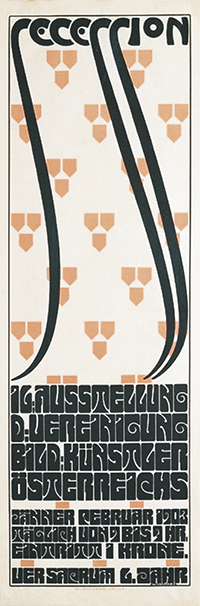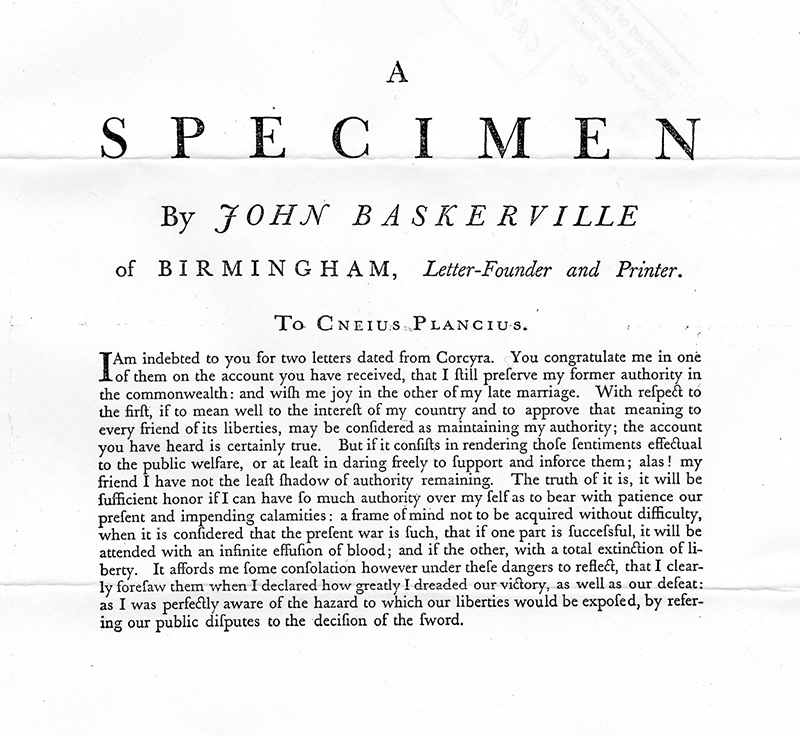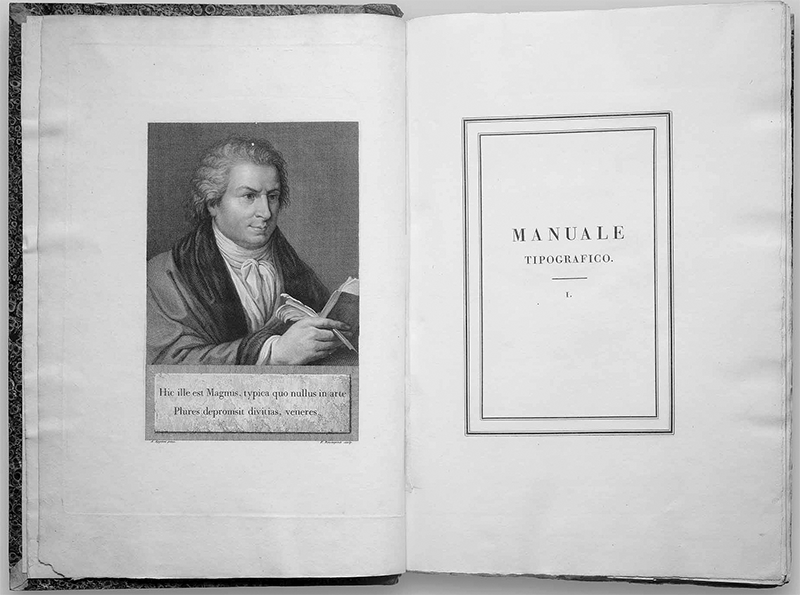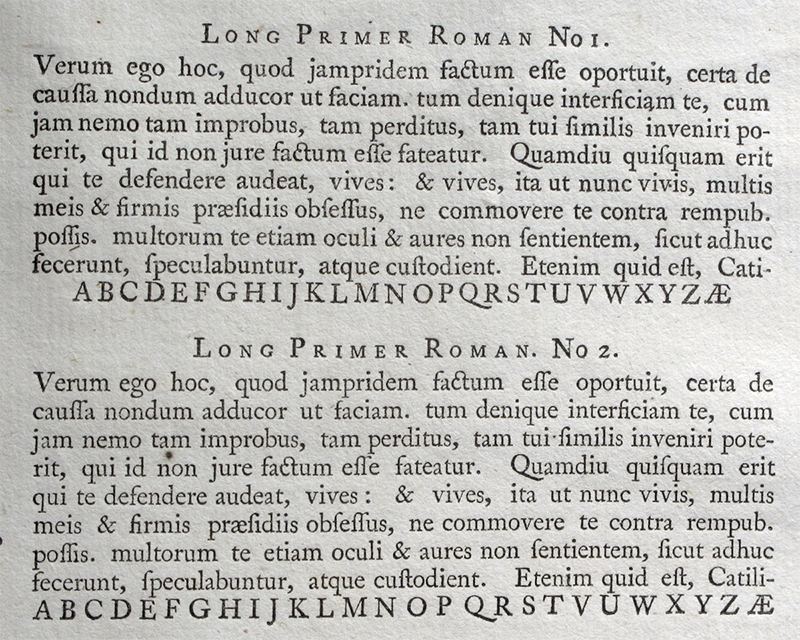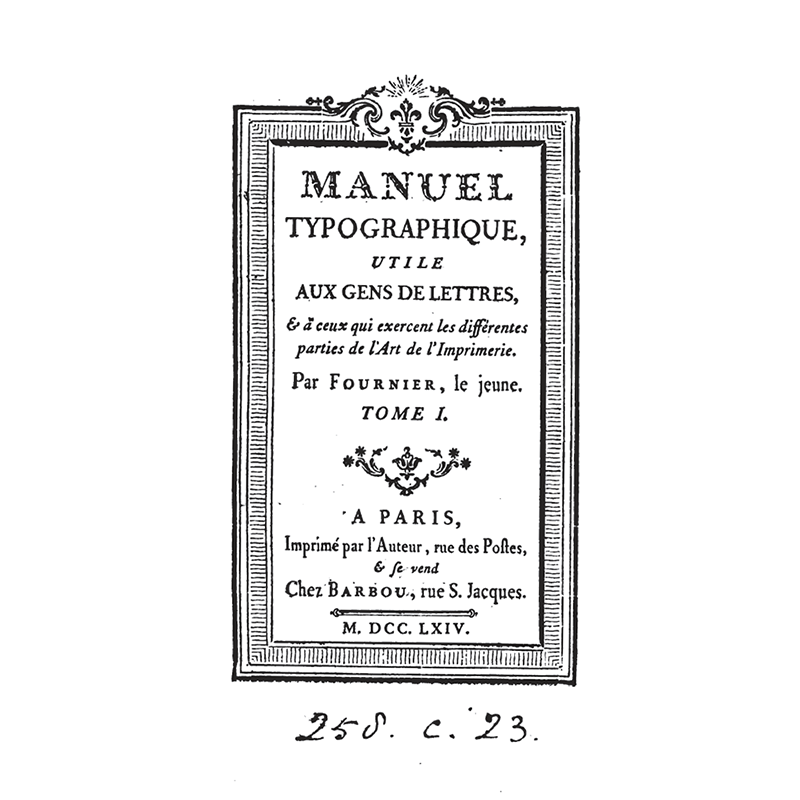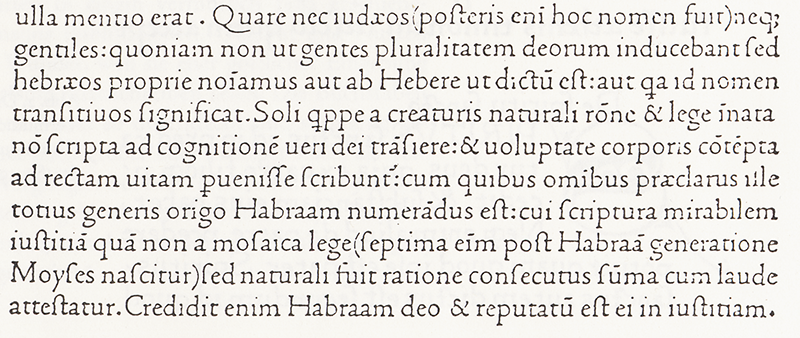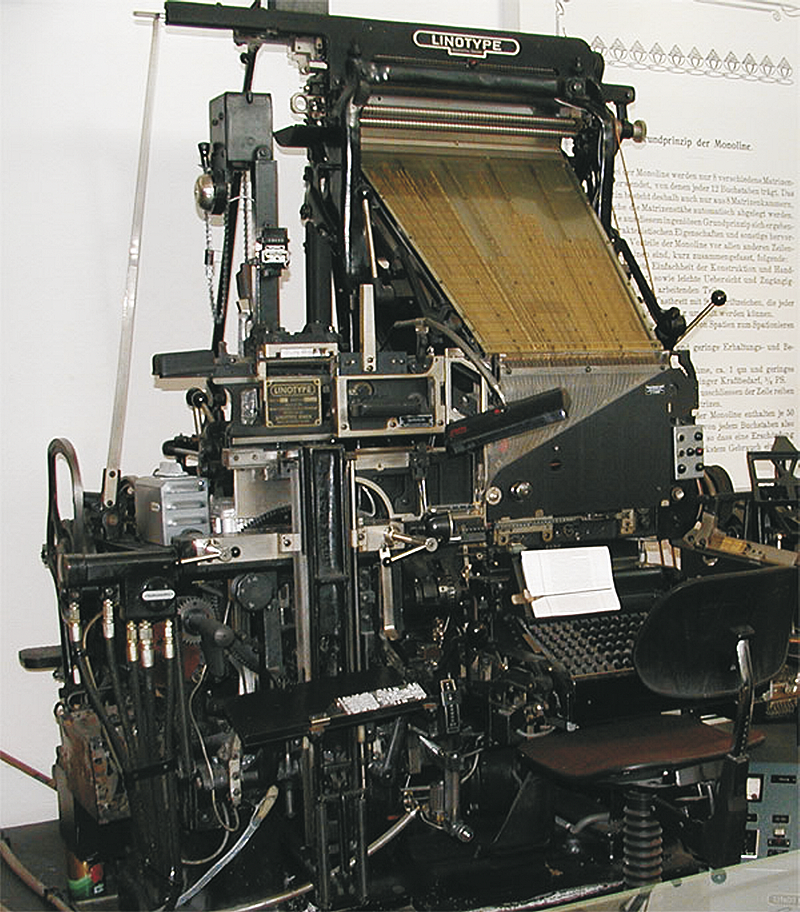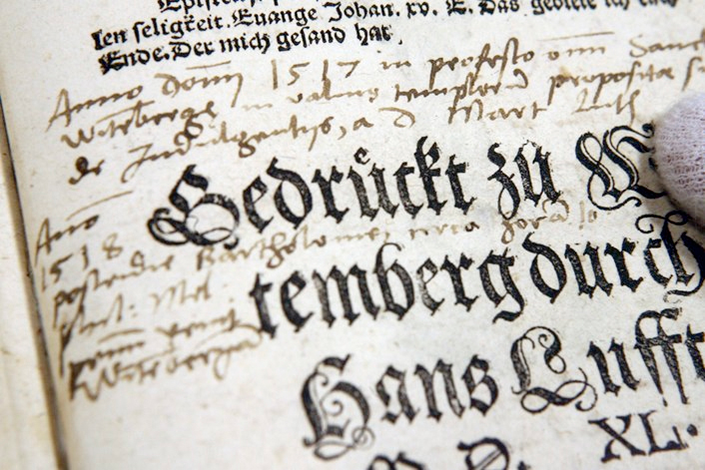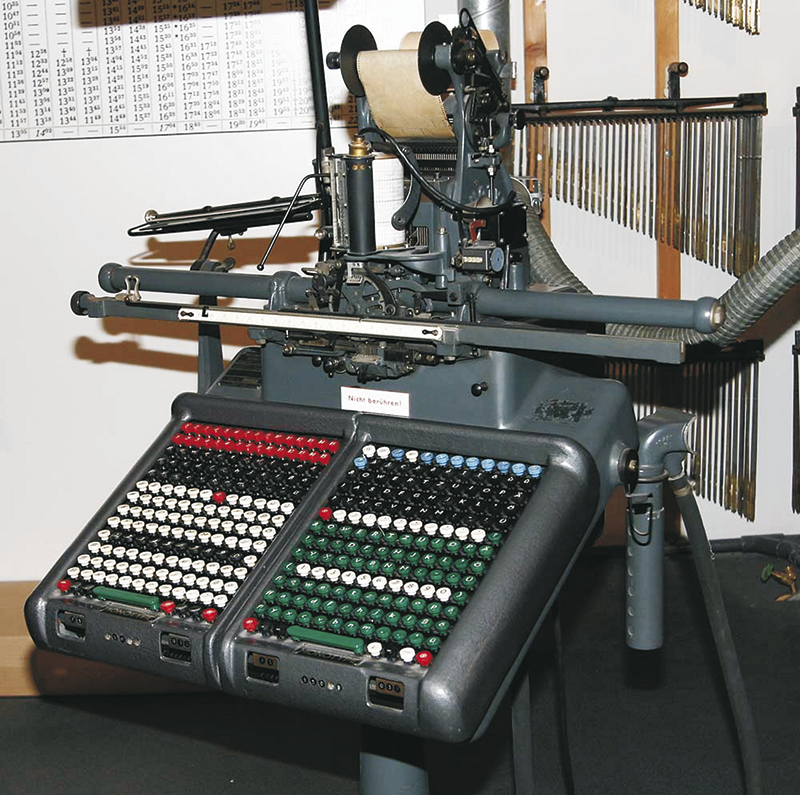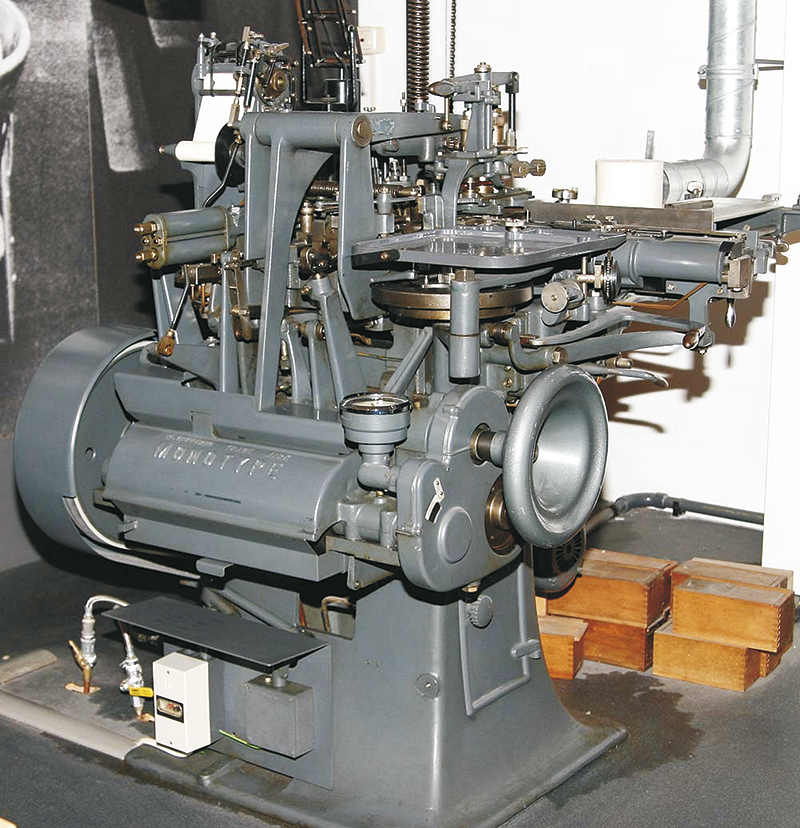
| Im Europa der Renaissance bilden sich neue Berufsbilder: die des Schriftschneiders und Schriftsetzers. Einige von den Schneidern erlangen bis in die Zeiten des digitalen Druckverfahrens so großes Ansehen, dass die von ihnen gegossenen Alphabete von den modernen Gießereien und Foundrys neu gezeichnet, gegossen bzw. digitalisiert worden sind: Jenson, Bembo, Garamond, Augereau, Granjon, Caslon u. a.
Die Schriftschneider der beginnenden Renaissance versuchen für die Buchstaben eine Form zu finden, die bestmögliche Lesbarkeit gewährleisten soll. Einige bemühen sich bei der Erstellung der Cancellaresca die Handschrift der Schreibmeister nachzuahmen: so entstehen die Kursivschnitte. Mehr dazu im Artikel Die Idee der beweglichen Letter verbreitet sich schnell in ganz Europa. Auf der Suche nach einer neuen Schriftform werden jedoch nicht die deutschen gebrochenen Schriften herangezogen, sondern die antiken Vorlagen der Capitalis für die Majuskeln, sowie die karolingische Minuskel verwendet. Die neuen Schriften besitzen starke kalligrafische, humanistische Züge, die ganz dem Geist der Renaissance entsprechen. Es werden Schriftzeichen entworfen, die ihresgleichen hinsichtlich der Lesbarkeit und der Form bis in die heutige Zeit suchen. Da die ersten mit dieser Schrift gedruckten Ausgaben häufig auch antike Werke der griechischen und römischen Philosophen beinhalten, ist der Name der Schriften auch bald gefunden: antiqua (lat. ‚antiquus‘ = das Alte, aus dem Altertum stammend). Im Zentrum der Innovation liegt Venedig; hier wirkt der Franzose Nicolas Jenson (1420–1480), der für das im Jahr 1470 erscheinende Buch „De evangelia praeparatione“ des Kirchenvaters Eusebius aus Cäsarea einen eigenen Schriftschnitt entwirft: die Jenson Antiqua, die durch den geneigten Querstrich der e-Minuskel und die markanten oberen M-Majuskel Abschlüsse die charakteristischen Merkmale der venezianischen Antiqua aufweist. |
Die ständigen Kämpfe auf der Halbinsel zwischen Spanien, Frankreich, Österreich, der Schweiz und den einzelnen italienischen Republiken stören die anfangs so erfolgreiche Entwicklung des Druckwesens in Italien. So verlagert sich das Zentrum der Schriftentwicklung nach Frankreich. Hier wirken u. a. Claude Garamont (1499–1561), Antoine Augereau (1485–1534), Robert Granjon (1513–1589) und Jean Jannon (1580–1658). Die Antiquas verbreiten sich mit der Idee des Protestantismus in den Niederlanden, der Schweiz und in England. Das Gedruckte kann zu einer Waffe im Propagandakrieg genutzt werden: das erkennen sowohl der König (Louis XIII. gründet in Louvre die „Manufacture royale d'imprimerie“ im Jahr 1640), wie auch die Kirche (s. die Machenschaften des Kardinal Richelieu rund um die Konfiszierung ganzer Schriftsätze berühmter protestantischer Drucker, Verleger, Schneider und Setzer). |
Erwähnenswert ist in diesem Zusammenhang, dass die Entwicklung der Schrift in den deutschsprachigen Ländern unterschiedlich zu den anderen Nationen verläuft. Während die meisten Länder Westeuropas aufgrund ihrer lateinischen Tradition Antiqua-Schriften einsetzen, bleibt Deutschland der gebrochenen Schrift – die den Entwicklungsprozess von der Textura über Schwabacher bis zur Fraktur durchläuft – jahrhundertelang treu. Teilweise wird dieser Zustand durch die Reformationsbewegung (1517 Luther in Wittenberg, dann Melanchthon, Zwingli, Bucer, Calvin, Anglikaner), den Druck von Propagandaschriften 30, sowie durch die Verwendung der Landessprache in der Liturgie und in den Übersetzungen der Bibel in diese Sprachen, begünstigt. Die Antiqua wird als die Hausschrift des Erzfeindes – der katholischen Kirche – gesehen. Die Fraktur wird in den deutschsprachigen Ländern bis zum Ende des II. Weltkriegs vorwiegend als Gebrauchsschrift genutzt, die Antiqua dient lediglich den Auszeichnungszwecken. |
Die Bücher der Barockzeit spiegeln mit den üppigen Formen und der ausufernden Ornamentik den Geist der gesamten Epoche wider. Nicht desto trotz – geprägt vor allem durch die französischen, niederländischen und englischen Schriftschneider – entstanden in dieser Zeit einige neue, qualitativ hochwertige Schriften. Zu den bedeutendsten Typographen der Barockzeit gehörten Philippe Grandjean (1666–1714), Johann Michael Fleischmann (1701–1768), Christoffel van Dyck (1605–1669), William Caslon (1692–1766) und John Baskerville (1706–1775). Durch die Verfeinerung der Radiertechnik der Barock- und der Rokokozeit, sowie durch die Einführung des Kupferstichs sind im Klassizismus sehr kontrastreiche, von sehr dünnen bis zu sehr dicken Linien geprägte Schriften möglich. Sie sind nicht so gut lesbar wie die Antiquaschriften und der feine Strich (nicht besonders strapazfähig) erlaubt nur den Druck von eher kleinen Auflagen. Die klassizistischen Alphabete zeigten eine gewisse „Eleganz, Präzision und Souveränität der Formen”. 31 |
Es findet auch ein Wechsel von der dynamisch-asymmetrischen zu der statisch-symmetrischen Form statt. Der sehr sparsame Einsatz der Ornamentik, der Ersatz der Initialen durch etwas größere Versalien der Brotschrift, der Blocksatz und die Mittelachse als Hauptformen des Layouts kennzeichnen die Drucksorten des Klassizismus. Die wichtigsten Typografen dieser Epoche: John Bell (1746-1831), Giambattista Bodoni (1740–1813), Pierre Simon Fournier (1712–1768), Familie Didot (Firmin Didot 1689–1757), Johann Friedrich Unger (1753–1804) und Justus Erich Walbaum (1768–1837) . |
Auf die klaren Linien des Klassizismus folgte der exzessive Dekorationswahnsinn des Historismus. Diese Epoche „bediente sich der stilistischen Zitate und Verzierungen von der Antike über die Gotik bis zum Rokoko. (…) Dies alles geschah rein formal, weil die vorfabrizierten Verzierungen ohne jeglichen inhaltlichen Bezug verwendet wurden: in der Architektur sahen Fabriken aus wie griechische Tempel, im gedruckten Bereich sahen Briefbogen und Rechnungen aus wie Ankündigungen zum Ritterschlag, Geschäftsanzeigen wie Denkmale. Zeilen und Texte waren auf Mittelachse ausgerichtet in weitschweifigsten Schriftphantasien gesetzt. Es ist überraschend, dass die gestalterische Kultur des Historismus, die hundert Jahre lang bekämpft, bespöttelt und überwunden wurde, in modernisierter Form durch die neuen Techniken, in der DTP-Typografie (1990) und in der multistilistischen Typografie (1995) erneut aktuell ist. Der Stil war damals und ist heute ein ängstliches Aufbegehren des bewegten künstlerischen Individuums vor befürchteter normierter Enge.“ 32 |
William Morris (1834–1896), einer der Gründer der „Arts and Crafts” Bewegung, sowie die meisten Kritiker und Typografen seiner Zeit waren sich einig, dass der Stil des Historismus den Verfall der Qualität bedeutet. Es sind in dieser Zeit jene Begriffe wie „Lesbarkeit der Schrift” oder „Geschlossenheit der Buchseite” wieder erfolgreich in die Praxis umgesetzt worden. Die Typografie orientiert sich wieder an den Vorbildern der Renaissance: die Golden Type der Kelmscott Press (1891) geht auf Nicolas Jenson zurück. Nicht nur das Schriftbild, sondern auch andere Elemente wie Ornamentik, Linie, Initialen, Illustration, Papier, Druck und Bindung werden bei der Produktion eines Druckwerkes berücksichtigt und abgestimmt. Das ausgehende XIX. Jahrhundert ist durch den Jugendstil gekennzeichnet. Geprägt ist diese Zeit durch die Sehnsucht nach Schönheit und Individualität, die abstrahierenden Formen finden ihre Vorbilder häufig in der Natur. Es wurden ganze Alphabete neu entworfen, die dem kompositorischen Ganzen untergeordnet worden sind. Die populärsten Medien für Druckbotschaften waren Zeitschrift und Plakat, die den Formenreichtum der Epoche oft prunkvoll darstellten. |
Es wurde versucht, einige der Erfindungen und Entdeckungen des XIX. Jahrhunderts auch in der Drucktechnologie anzuwenden. Die Methode des Handsatzes ist seit Gutenberg (~1440) bis zum Einsatz der ersten mechanischen Setzmaschine Linotype 1886 von Ottmar Mergenthaler unverändert geblieben. In vielen Druckbetrieben wurde der Handsatz mit Bleilettern bis in die 50er Jahre des XX. Jahrhunderts immer noch angewandt. Die Linotype wurde mit großer Begeisterung in der Branche aufgenommen – um 1900 waren 6.000 Maschinen im Einsatz.34
„Die erste Ausführung, die ‚Blower Linotype‘ wurde 1886 bei der Zeitung ‚New York Tribune‘ vorgeführt. Mit dieser Maschine ließen sich ganze Zeilen auf einmal gießen. Bei der auch kurz als Blower bezeichneten Maschine wurden Matrizenscheiben über ein Luftgebläse zum Sammler geführt. Die Linotype wurde im Lauf der Zeit immer weiterentwickelt und verfeinert. So ließ sich Mergenthaler seine Weiterentwicklung ‚Simplex‘ Anfang 1888 unter dem Namen Linotype patentieren. Bei späteren Modellen werden die in Magazinen aufbewahrten Matrizen der einzelnen Drucktypen über eine schreibmaschinenähnliche Tastatur in der gewünschten Reihenfolge ausgelöst und zum Sammler weitergeleitet. Die zu Zeilen aneinander gereihten Matrizen gelangen anschließend in den Gießapparat, wo auch das Ausgleichen der Wortzwischenräume für die gewünschte Zeilenbreite, bzw. das Ausschließen, erfolgt. Nach erfolgtem Guss und Ausstoß der kompletten Zeile werden die Matrizen dann an ihren jeweiligen Platz in den Magazinen zurückgeführt.“ 35 |